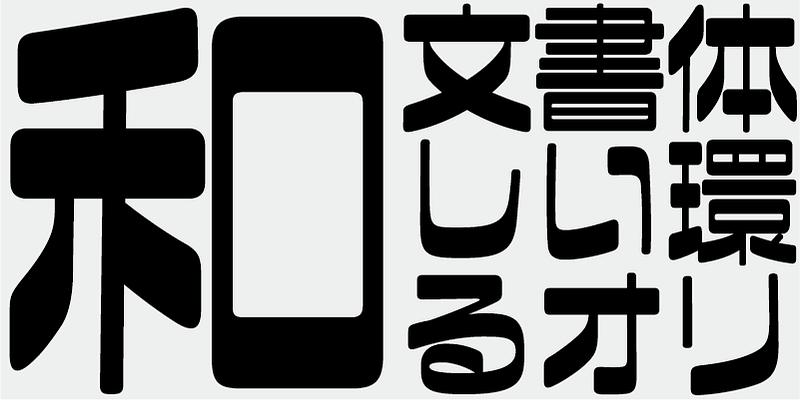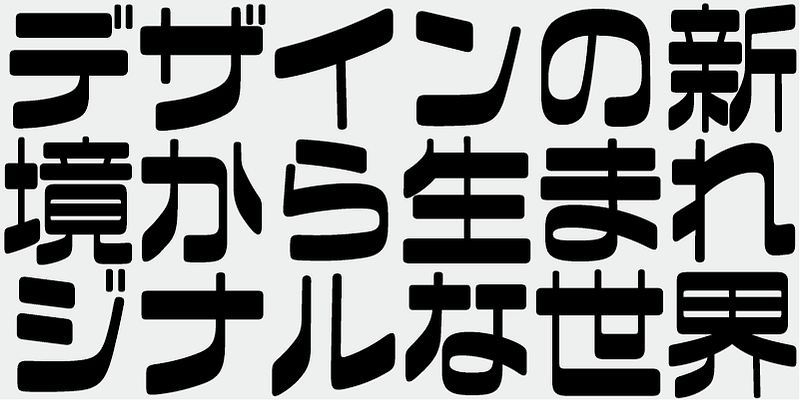
Shiguma est le nom du héros dans une bande dessinée de science-fiction. Cette police engendre la nostalgie de l’ère Showa avec un look rétro futuriste.
Cette police comprend les 1 000 principaux caractères kanji choisis à partir de tableaux de fréquence de caractères établis par des sociétés de presse, des maisons d’édition et des instituts de recherche linguistique, ainsi que 206 caractères kana et signes de ponctuation.
Dans la production de polices japonaises d’aujourd’hui, les 7 000 caractères de la norme JIS sont considérés comme essentiels. Mais toutes les polices ont-elles vraiment besoin de 7 000 caractères ? À l’ère de la phototypie, on utilisait beaucoup moins de caractères. FONT1000, un groupe de typographes indépendants, a commencé par se focaliser sur cette simple question. Nous avons sélectionné le minimum de 1 000 caractères kanji (idéographiques) nécessaires pour la composition en japonais et créé activement des polices pour les prendre en charge. Ce jeu de 1 000 caractères kanji a été créé en étudiant des données de fréquence des caractères compilées par des sociétés de presse, des maisons d’édition et des organismes de recherche linguistique, etc. Il comprend également des caractères syllabiques kana et des signes de ponctuation. FONT1000 a été créée en 2001 avec 25 designers et 25 polices de caractères. Aujourd’hui, nous avons 130 polices et comptons désormais près de 40 membres, ce qui permet de travailler sur des polices avec plus de caractères.